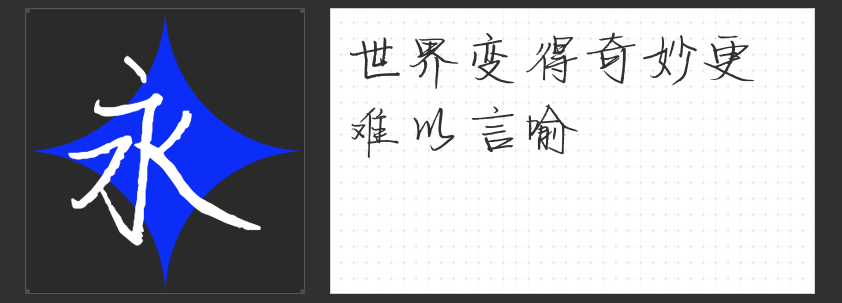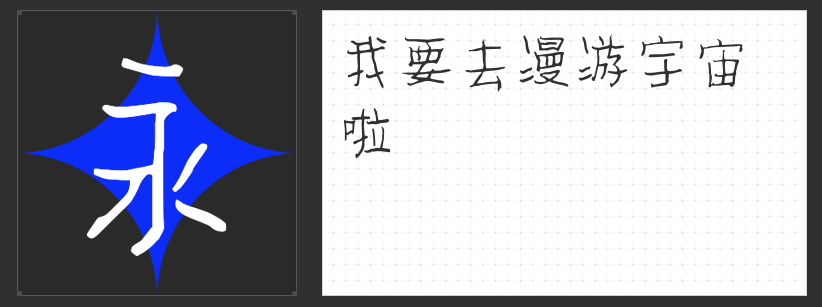
四款绝美手写字体推荐:让你的设计作品独具匠心
在字体设计的世界里,手写字体以其独特的韵味和个性深受设计师们的喜爱。今天,为大家推荐四款各具特色的手写字体,让它们将为你的设计作品增添一抹独特的魅力。
这款字体风格可爱、随意,仿佛是在日记本上随意挥洒的笔迹,充满了日常的气息。它的线条柔和,字形圆润,给人一种亲切、温暖的感觉。无论是用于个人博客、社交媒体还是手账制作,都能让你的文字瞬间变得生动有趣。
这款字体自由而不失个性,娟秀而整齐,非常适合多字排版。它的辨识度极高,实用性也很强,无论是用于海报设计、宣传册还是PPT制作,都能让你的文字内容更加突出,吸引观众的眼球。
这是一款用笔多变、清新飘逸的创意手写字体。它的结体自由、开合得当,笔画间牵丝连带,展现了用笔的连贯性和流畅性。排版后的效果如同歌曲所带来的旋律,让人仿佛置身其中,感受情感的流露。这款字体非常适合用于海报宣传、广告设计、包装设计等应用场景,能够瞬间提升作品的艺术感和感染力。
这款字体的设计独具匠心,重心放低,内部留白空间不规则,圆弧形笔画被巧妙地处理为折角,让整个字体形态呈现方块状。这种独特的设计让字体看起来更加别致、有力量感,非常适合用于标题设计、标志设计或是需要强调文字个性的场合。